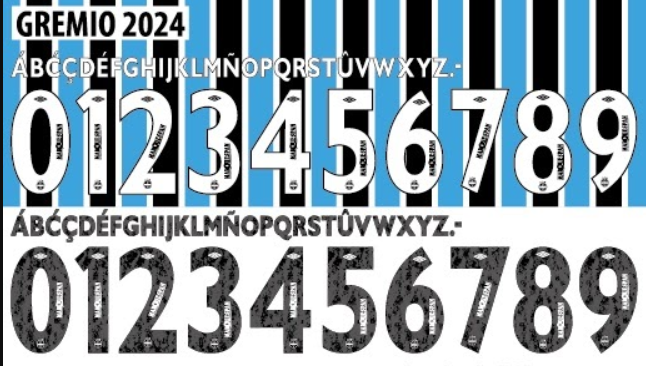
Seja para estampar o manto do Imortal Tricolor ou para criar artes digitais exclusivas, ter a tipografia correta é essencial. A temporada 2024 trouxe para a torcida gremista uniformes que mesclam a tradição das três cores com o design moderno da Umbro.
Estilo Visual e Aplicação
A tipografia desenvolvida pela Umbro para o Grêmio em 2024 segue uma linha estética robusta e geométrica, facilitando a leitura tanto no estádio quanto na transmissão televisiva.
Diferente de temporadas passadas que apostavam em curvaturas excessivas, a fonte atual preza por linhas retas e cortes angulares sutis, que harmonizam perfeitamente com as listras verticais da camisa titular e com a limpeza visual do uniforme reserva. É a escolha ideal para quem trabalha com personalização de camisas, mockups esportivos ou estampas de torcida.